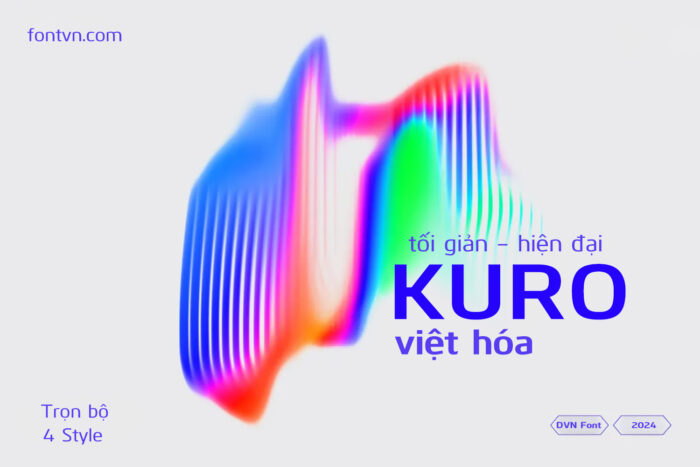
Bộ font Kuro Việt hóa – Font chữ Serif hiện đại, đẳng cấp cho nhiều dự án (6 Font)
Kuro là một kiểu chữ sans-serif hiện đại, nổi bật với các đường nét đơn giản, rõ ràng và sắc nét. Phù hợp cho cả in ấn và thiết kế kỹ thuật số, Kuro mang đến sự tinh tế và hiện đại cho các dự án thiết kế, đặc biệt trong các lĩnh vực như thiết kế đồ họa, giao diện người dùng và quảng cáo. Kiểu chữ này được thiết kế với tính chính xác cao, giúp tạo cảm giác cân đối và dễ đọc ở mọi kích thước. Kuro có nhiều trọng lượng khác nhau, từ nhẹ đến đậm, cung cấp sự linh hoạt tối đa cho người dùng trong việc lựa chọn phong cách và cảm xúc phù hợp với nội dung. Với các đường nét thanh lịch và tối giản, Kuro là lựa chọn lý tưởng cho các tiêu đề, văn bản ngắn, và cả các đoạn văn dài khi cần sự rõ ràng, không gây rối mắt nhưng vẫn giữ được tính chuyên nghiệp.